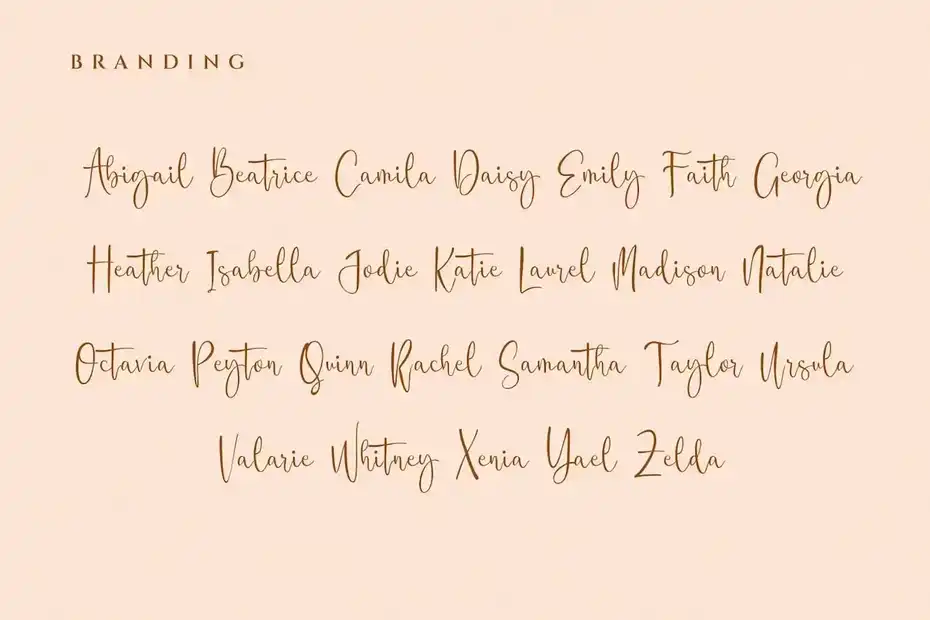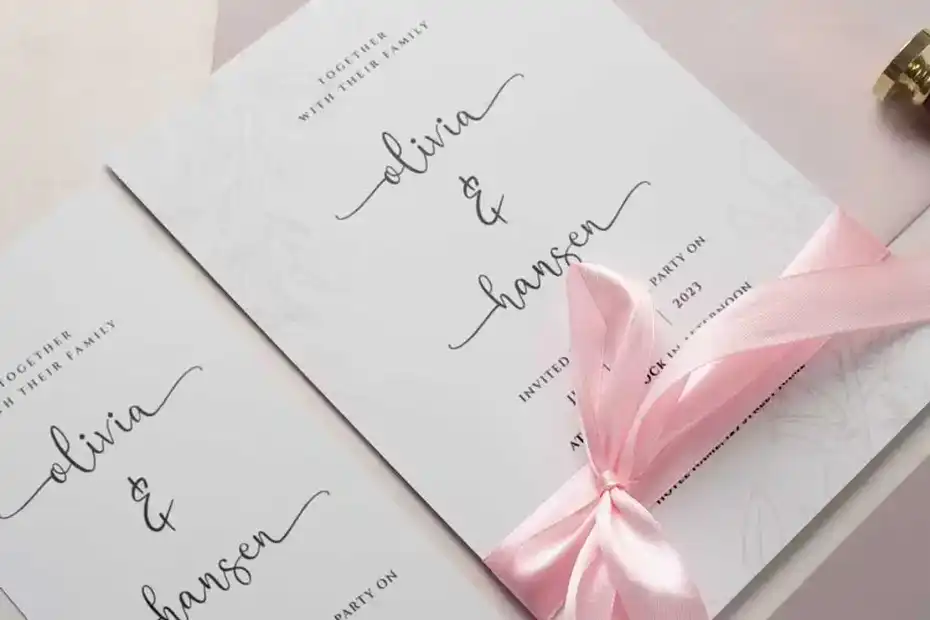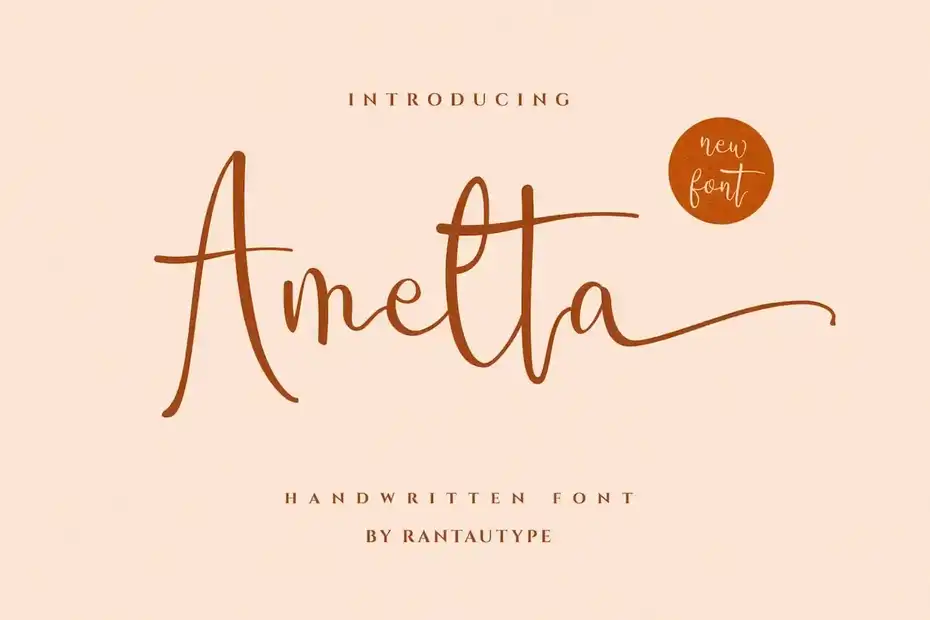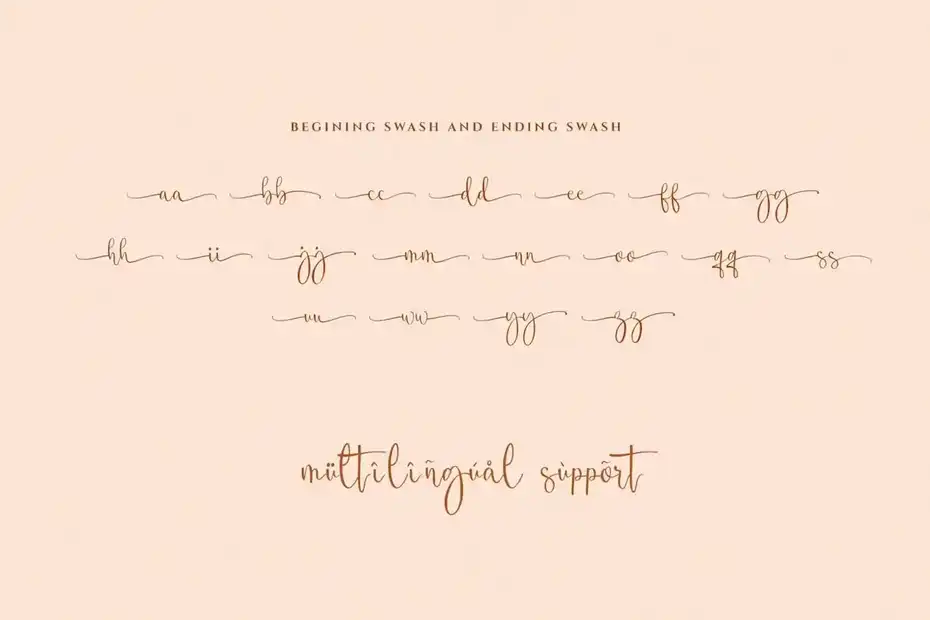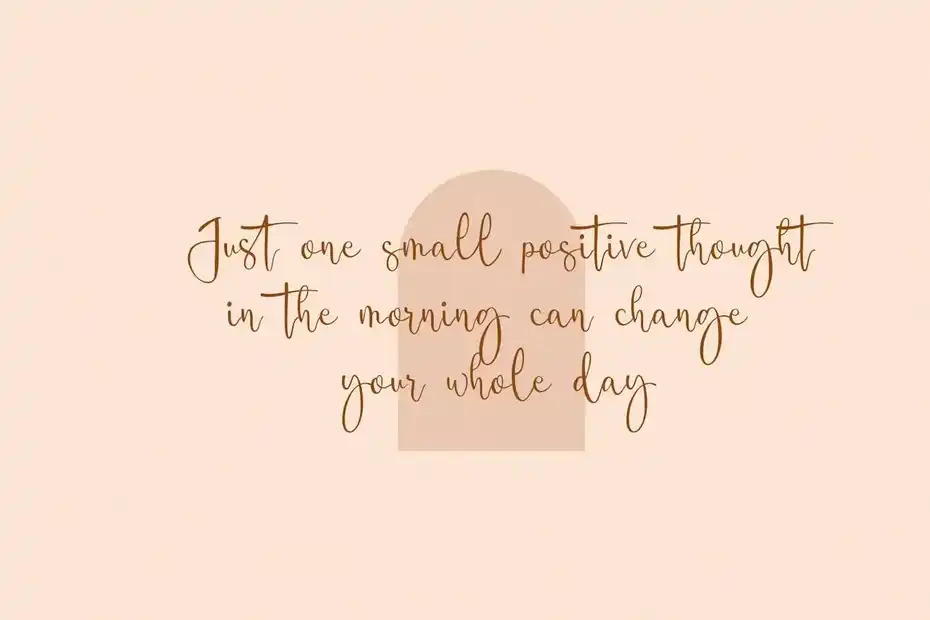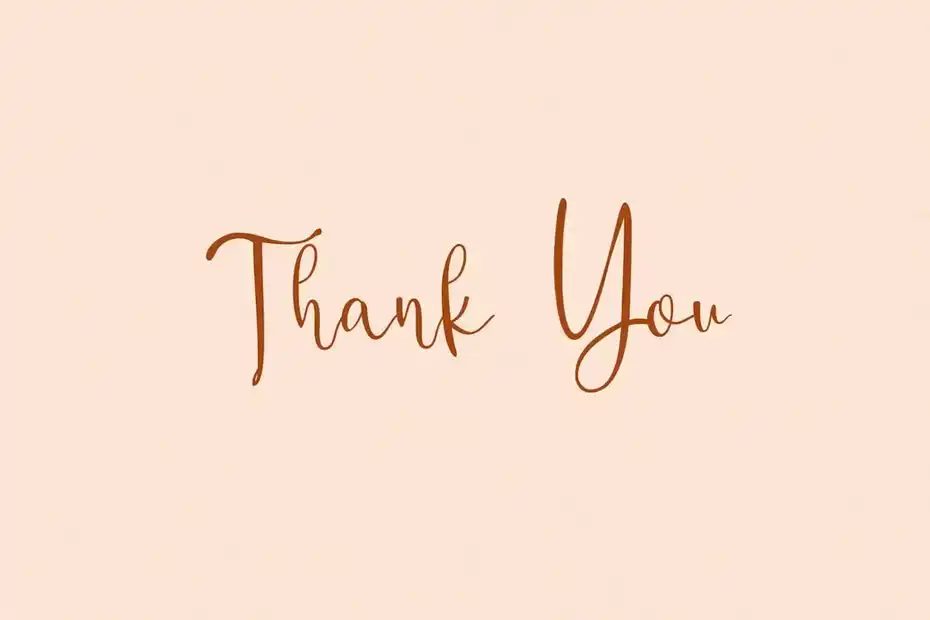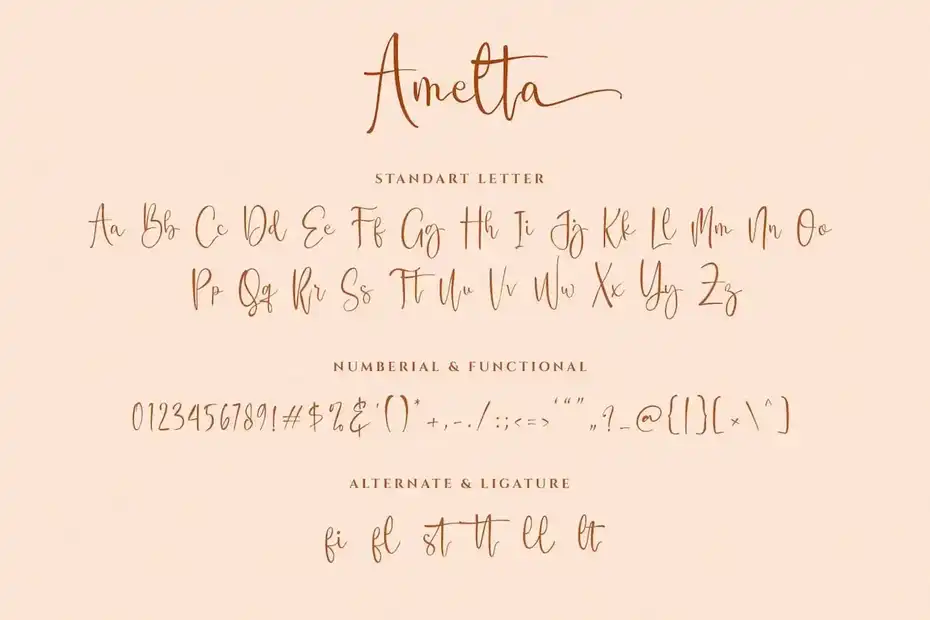
دانلود فونت انگلیسی دست نویس Amelta Handwritten font
فونت انگلیسی دست نویس Amelta Handwritten font : این مجموعه شامل فونت انگلیسی دست نویس است که برای امضا، لوگو، برندینگ، کارت دعوت عروسی، کارت ویزیت، نقل قول، کاور آلبوم و غیره مناسب میباشد.
• عنوان مجموعه: Amelta Handwritten font